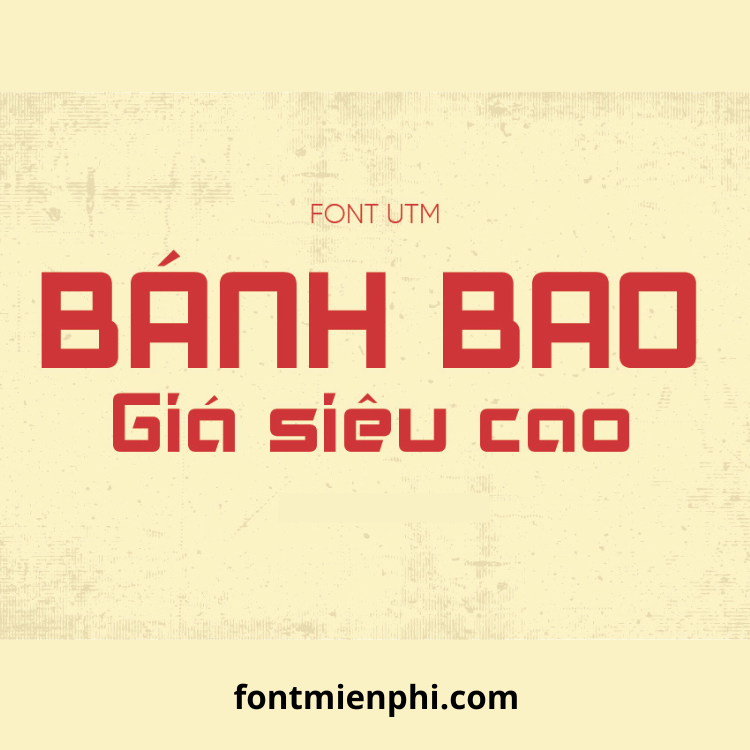
Việt hóa font UTM Akashi
Font UTM Akashi Việt Hóa – Tải Miễn Phí & Chất Lượng Cao
Giới Thiệu Font UTM Akashi Việt Hóa
Font UTM Akashi là kiểu chữ sang trọng, thanh lịch, phù hợp với thiết kế thời trang, logo, bao bì và các ấn phẩm cao cấp. Bản Việt hóa UTM Akashi trên Fontmienphi.com đã được tối ưu đầy đủ bộ dấu tiếng Việt, giúp bạn thoải mái sáng tạo mà không lo lỗi font.
Đặc Điểm Nổi Bật Của Font UTM Akashi
✔ Hỗ trợ tiếng Việt chuẩn Unicode – Đọc và viết mượt mà.
✔ Phong cách hiện đại, thanh thoát – Phù hợp thiết kế thời trang, nhãn hiệu.
✔ Nét chữ mảnh, sắc sảo – Tạo điểm nhấn cho banner, poster.